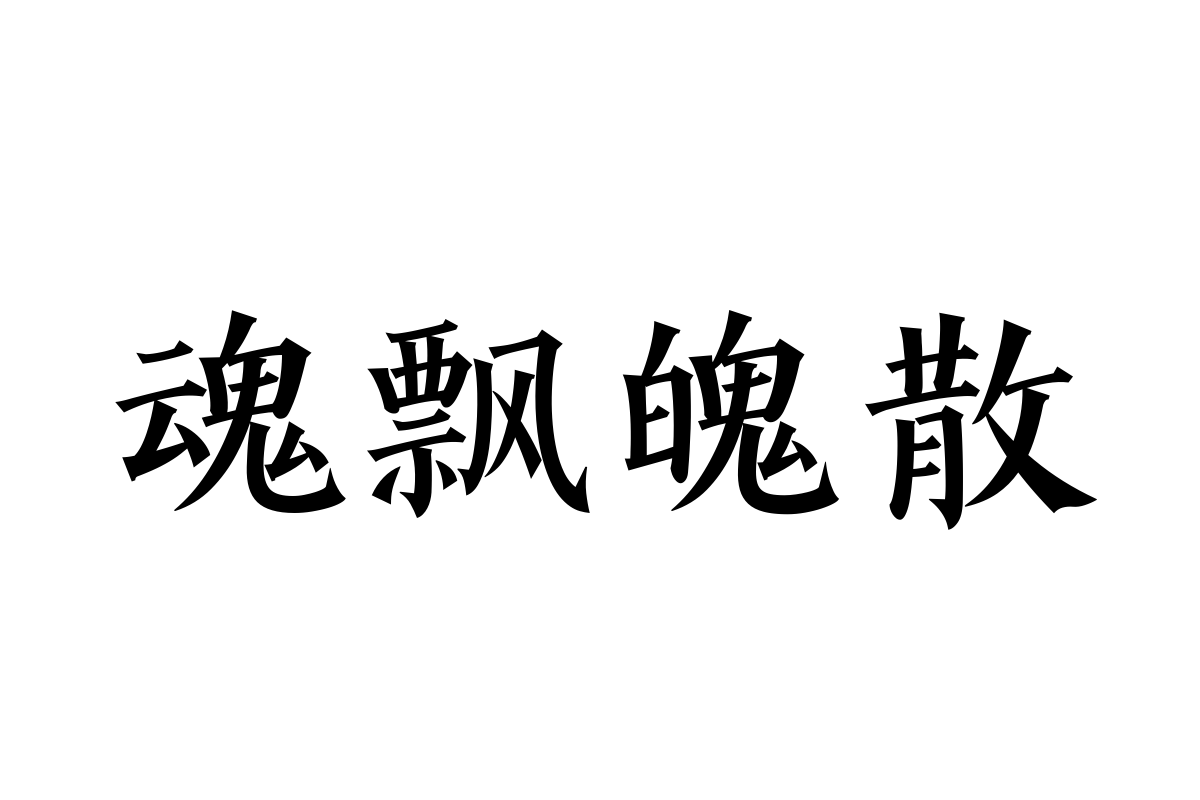
汉仪风骨楷体字体是一款具有独特风格的中文字体,它以简洁、硬朗的线条和结构为特点,给人一种强烈的视觉冲击力。这款字体适用于需要展现专业、严谨氛围的设计场景,如商务报告、学术论文等。
汉仪风骨楷体字体的特点如下:
1. 字形结构:汉仪风骨楷体字体的字形结构紧凑,笔画粗细适中,易于阅读和识别。同时,它的字形呈现出一种独特的风格,使得整体视觉效果更加统一和协调。
2. 线条流畅:这款字体的线条流畅自然,没有过多的装饰性元素,给人一种简洁、大方的感觉。这使得它在各种设计场景中都能展现出良好的视觉效果。
3. 适应性强:汉仪风骨楷体字体适用于多种设计场景,包括标题、正文、广告、包装等。无论是在印刷品还是数字媒体上,都能保持良好的视觉效果。
4. 易用性:汉仪风骨楷体字体的笔画结构简单明了,易于学习和使用。设计师可以根据自己的需求选择合适的字号和排版方式,轻松实现设计效果。
总之,汉仪风骨楷体字体是一款具有独特风格和广泛应用前景的中文字体。它以其简洁、硬朗的线条和结构,为设计师提供了一种全新的视觉表达方式,能够满足不同设计场景的需求。